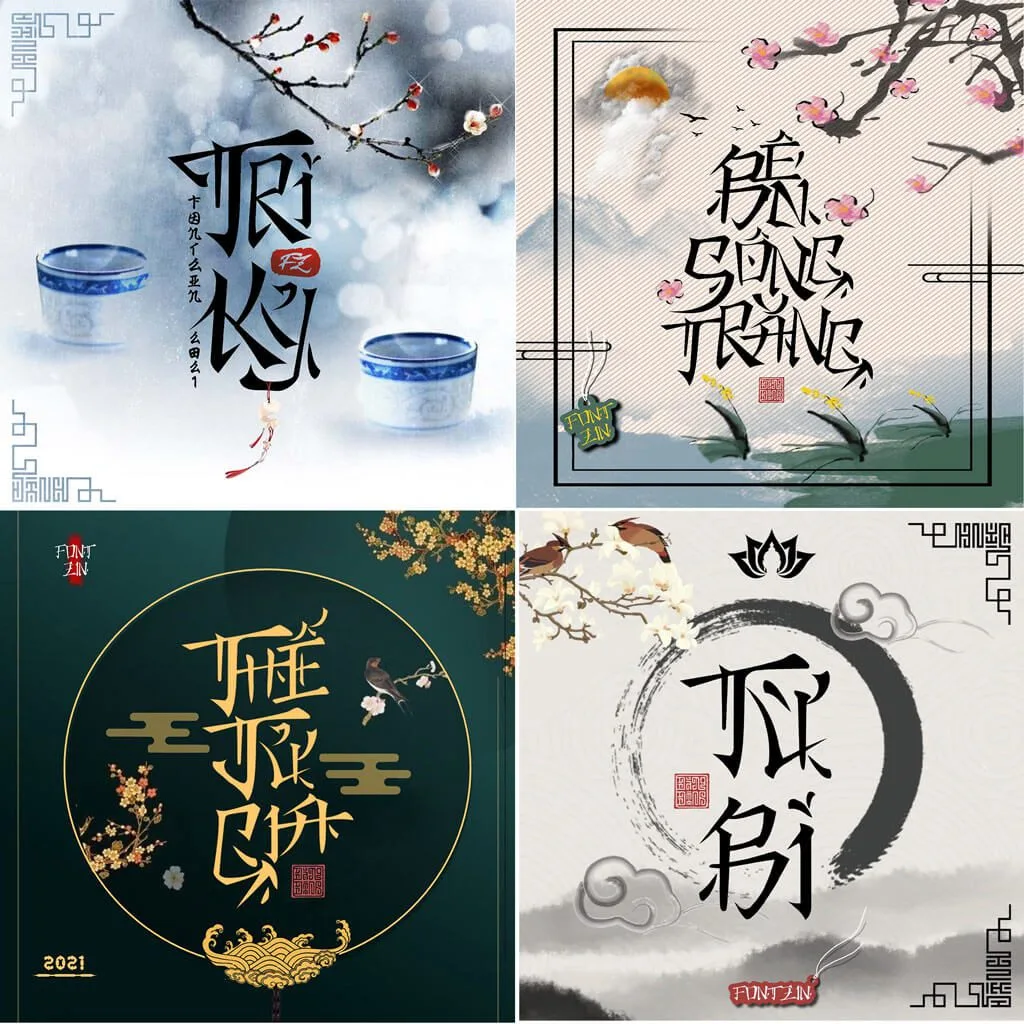
Font cổ trang việt hóa Fz002: Với những đường nét đậm chất văn hóa Nhật Bản và Trung Quốc. Bạn có thể dùng font chữ này để thiết kế truyền thống, cổ trang nhất là làm các tiêu đề cho video dạng cổ truyền, truyện tiên hiệp.
Giới thiệu font cổ trang Fz002
Tiền thân của font chữ cổ trang này là bộ vector trên Shuterstock có ID là 466020662. Vector này được thiết kế bởi Gleolite, Admin Đức Thủy đã mua và tiến hành thiết kế thành font chữ đặt tên là Fz002.
- Font mang phong cách chữ Hanzi và kanji nên phù hợp với những phong cách design cổ trang và màu sắc cổ điển theo văn hóa Nhật Bản và Trung Hoa.
- Với những đường nét đậm chất chữ Hanzi và kanji, khi nhìn vào lần đầu tiên bản sẽ liên tưởng đến đất nước xứ phù tang, xứ sở của hoa anh đào.
Với phong cách đặc biệt của typeface này Đức Thủy và FzTeam đã kỳ công thiết kế và tạo ra nhiều kiểu glyph độc đáo hơn nhằm tô điểm thêm cho nguồn font tiếng Việt nhiều nét mới lạ và độc đáo hơn.
Typeface Fz002 thiết kế hoàn thiện với các đặc điểm và tính năng sau.
- Đầy đủ các kí tự Latin, số và các ký tự tiếng Việt dựa trên dữ liệu vector 466020662.
- Kí tự chữ hoa, chữ thường được giữ nguyên theo phong cách và quy chuẩn như vector.
- Thêm 1 bộ glyphs dạng outline nhằm tạo hiệu ứng khác biệt và thanh thoát hơn khi bạn đặt ở cùng 1 vị trí với font gốc.
- Add thêm một số feature liga nhằm tối ưu các phụ âm và vần ghép trong Tiếng Việt.
- Tiếng Việt đã được kerning đầy đủ 100%, giúp bạn không cần phải căn chỉnh nhiều khi gõ nội dung.
Font cổ trang Việt hóa Fz002 thích với các chủ đề truyền thống.
- Fz002 đặc biệt thích hợp với những dự án thiết kế cần sắc thái, phong cách Nhật Bản, Trung Quốc, Hàn Quốc.
- Nếu bạn thường thiết kế về chủ đề văn hóa châu Á thì Fz002 là một lựa chọn không thể bỏ qua.
Font Fz002 có những đặc điểm gì?
Font Fz002 có đầy đủ ký tự Latin, số, tiếng Việt, glyphs dạng outline, feature liga, kerning tiếng Việt 100%.
Font Fz002 phù hợp với chủ đề nào?
Font Fz002 phù hợp với phong cách thiết kế cổ trang Nhật Bản, Trung Quốc và Hàn Quốc.